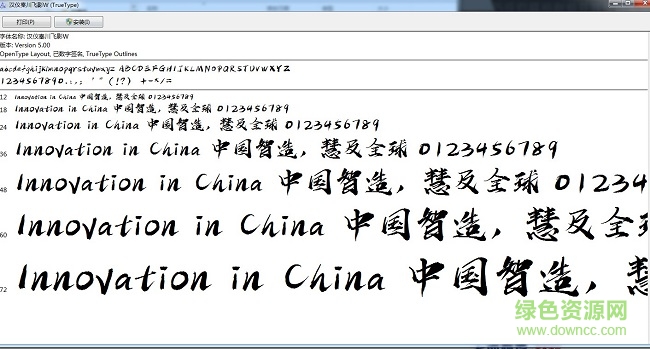
汉仪秦川飞影w
汉仪秦川飞影w是一款带有古典气息的汉仪字体,外形和手书体有点像,线条张扬肆意,富有动势,特征鲜明,可以用在中国风的海报设计方面,喜欢的朋友快来下载吧!
中文书法字体介绍
【楷书】:形成于东汉。字体方正,规矩严整。
【行书】:兼有楷书和草书的长处,既工整清晰,又飞洒 活泼。
汉仪秦川飞影
【草书】:起源于汉 初,成熟于东晋。写意性发挥到极 致,变化丰富,奔放跃动。
【小篆】:始于秦代。字体 略长,笔画圆匀,富于图案美。
【隶书】:始于秦朝,成熟并通行于汉魏时 代。字体宽扁,左右舒展,平衡对 称,整齐均匀。